「対」の見本。
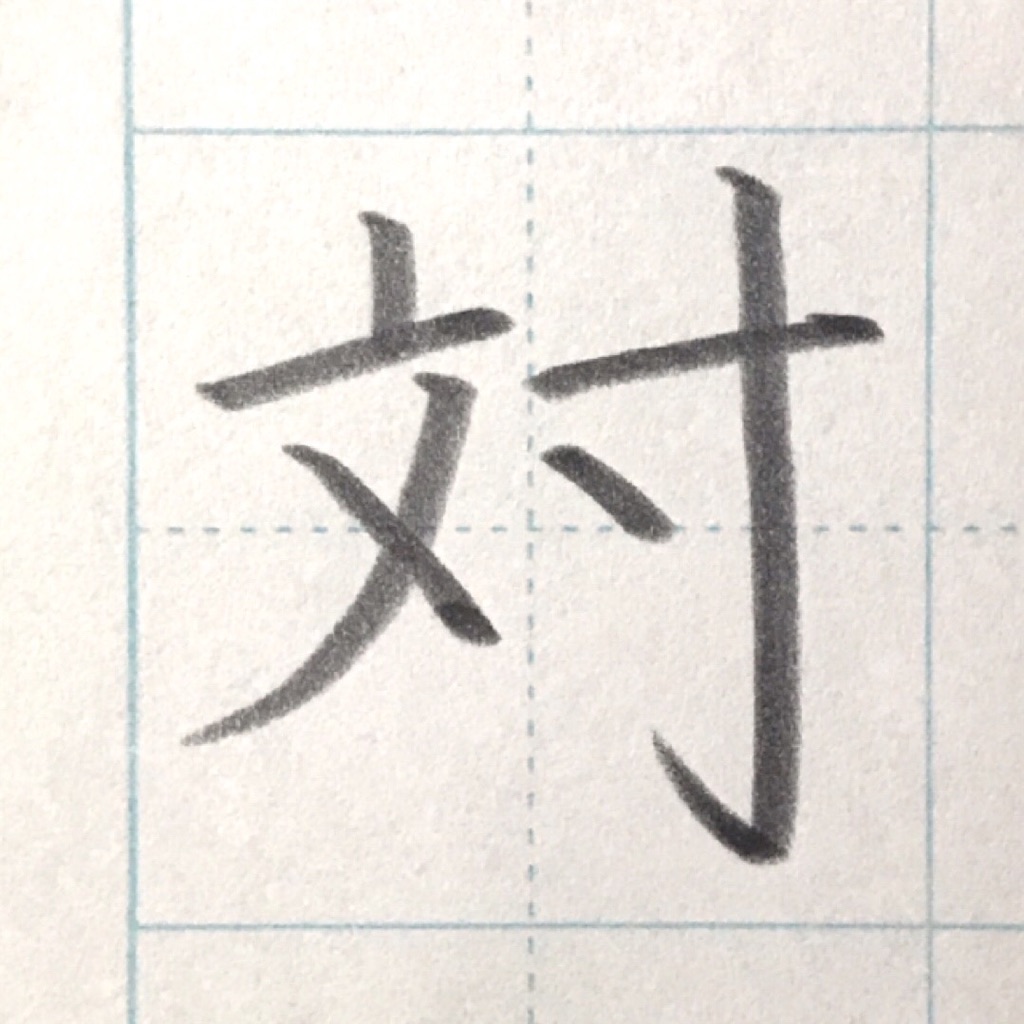
「対」の書き順。
7画です。
「対」のポイント。
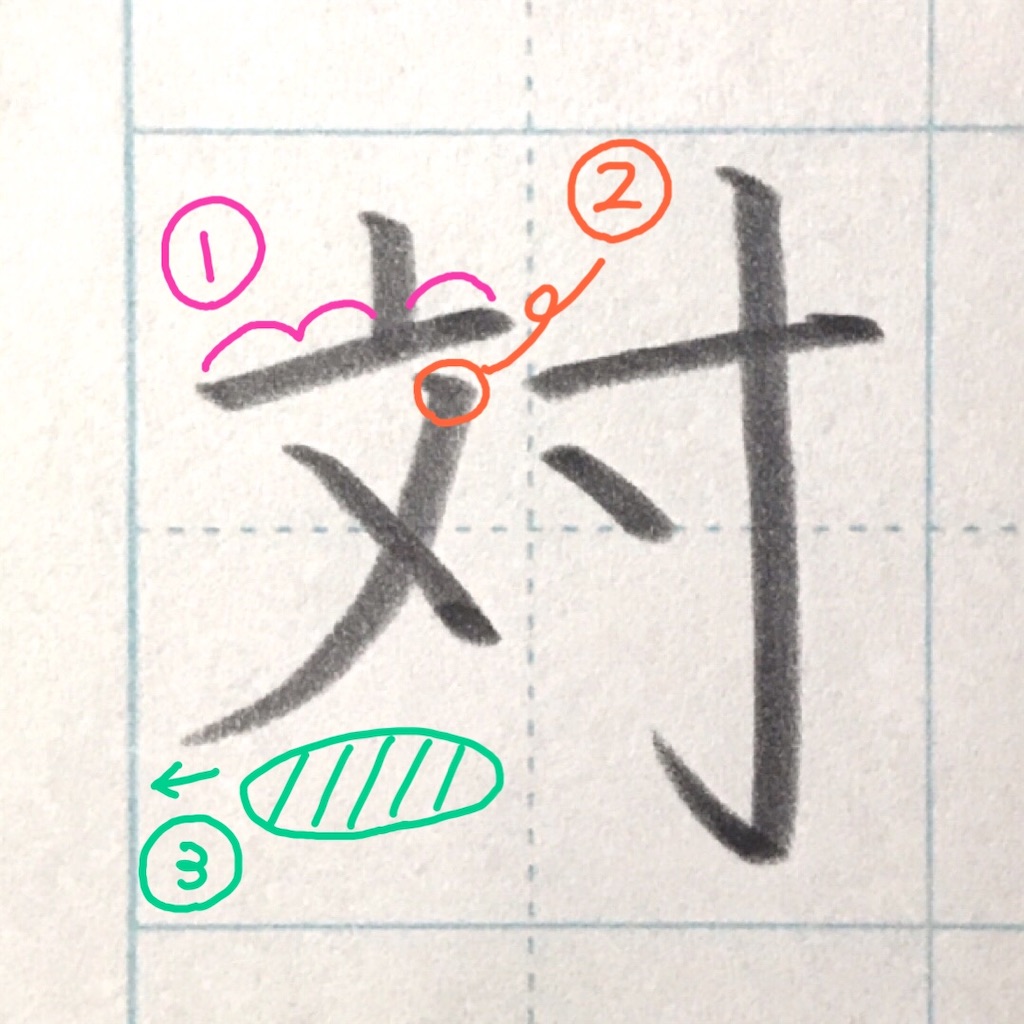
①2画目と2対1になるように、1画目の点は少し右に寄せる。
②3画目は2画目の右端からスタート。
③3画目、下に余白を作ることを意識。
最後は横に向けて払うと良いです。
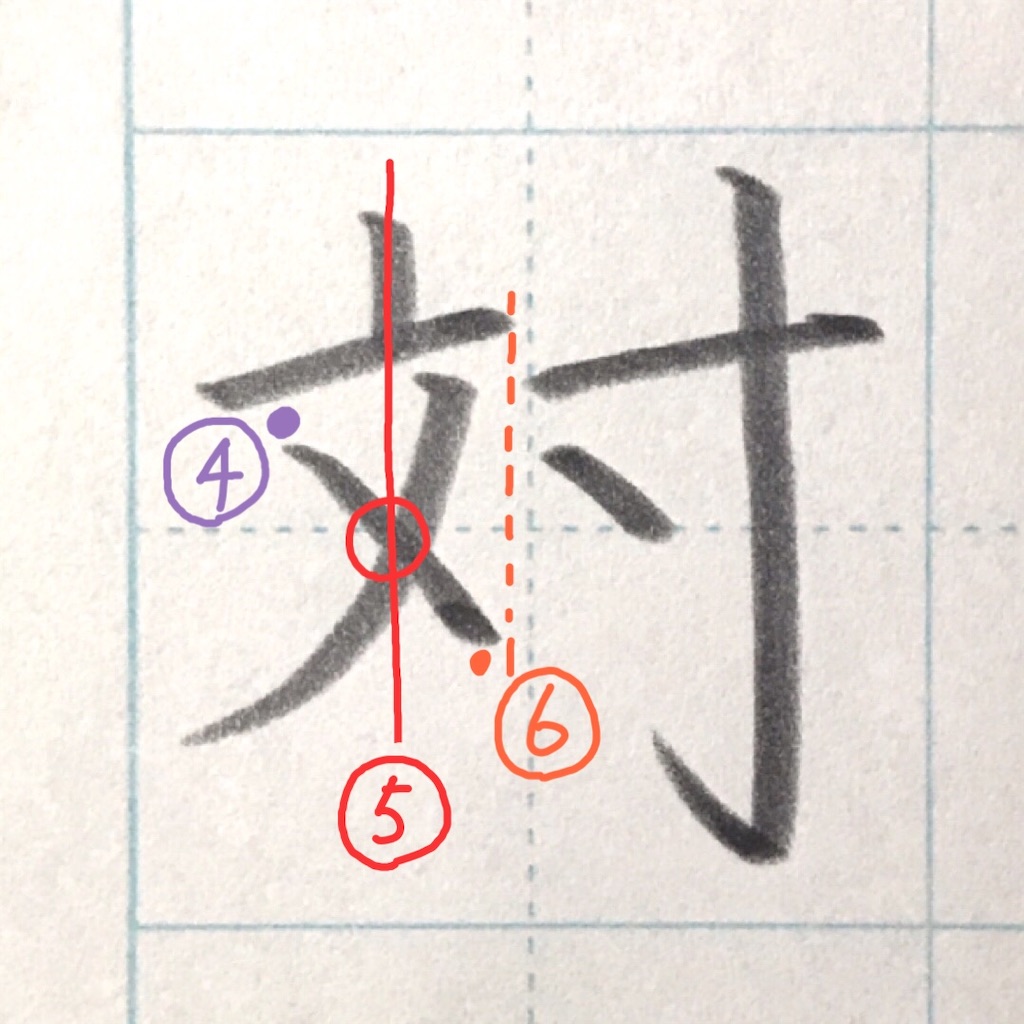
④少し空ける。
⑤1画目と3・4画目の交点がまっすぐになるように。
⑥4画目、右にはみ出さないように、しっかりと止めます。
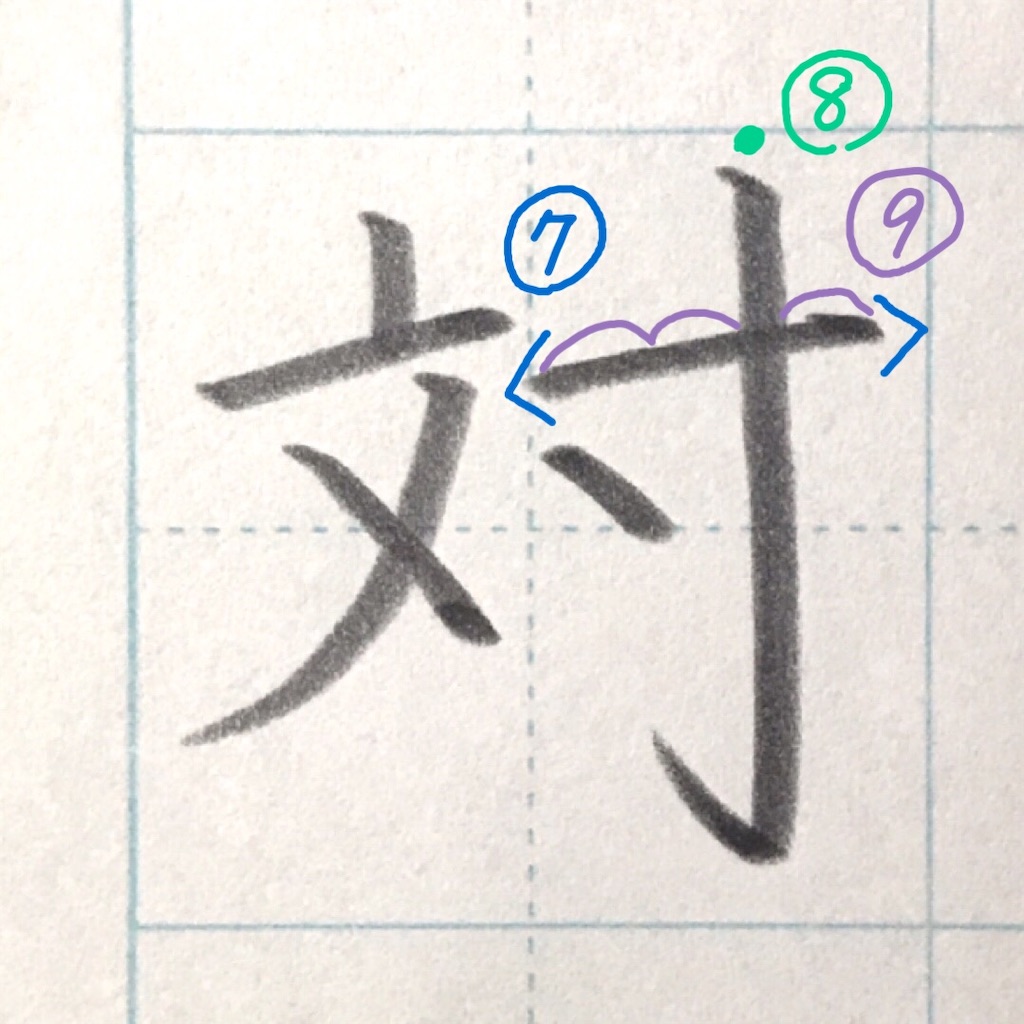
⑦5画目、2画目の横画よりも少し下からスタート。
★横画は右上がりに揃えましょう!
⑧1画目よりも高くする。
⑨2対1になるように縦画を通す。
曲がらないように注意。
⑩点に向けて、しっかりとハネます。
45度くらいが◎。
⑪左端を揃える。
完成!